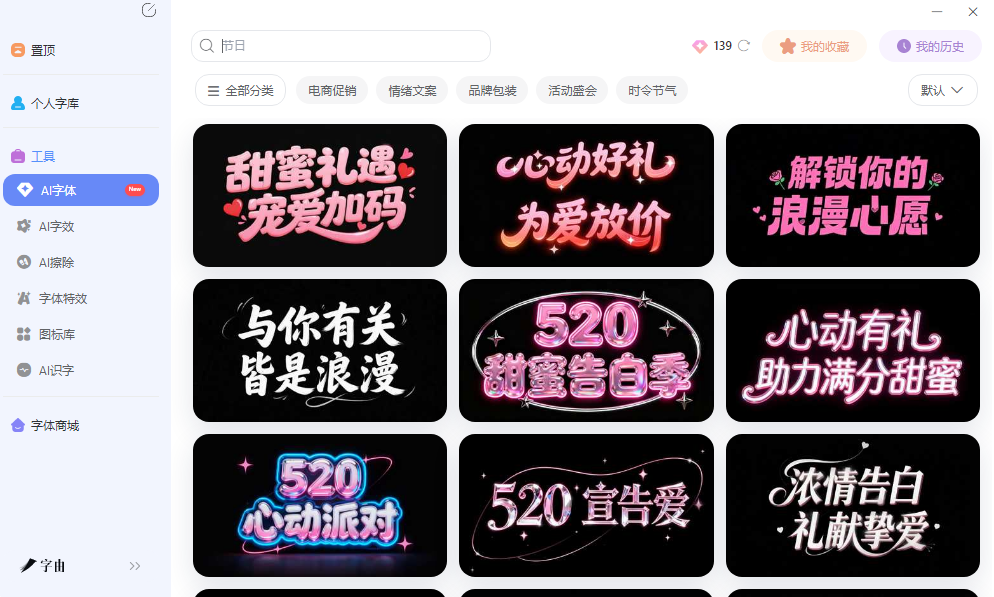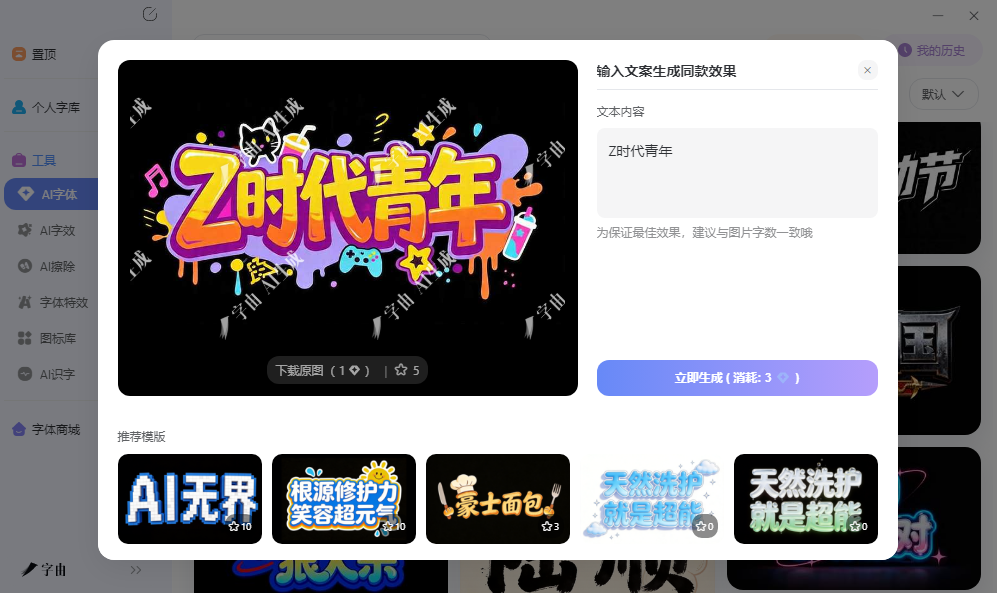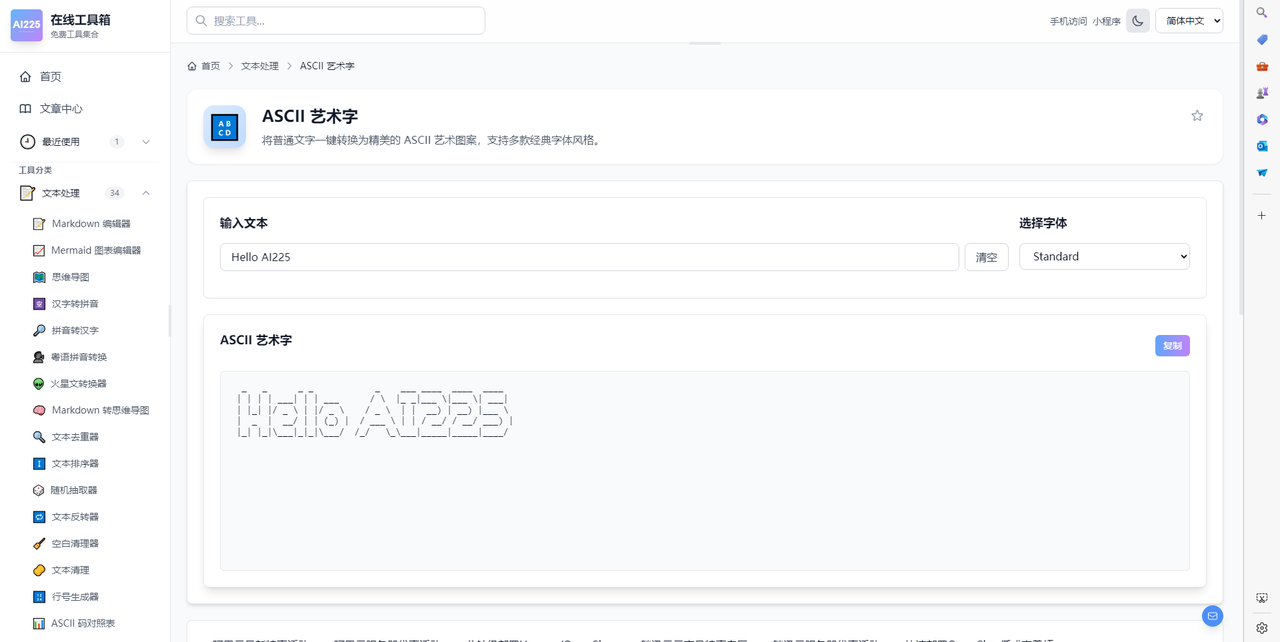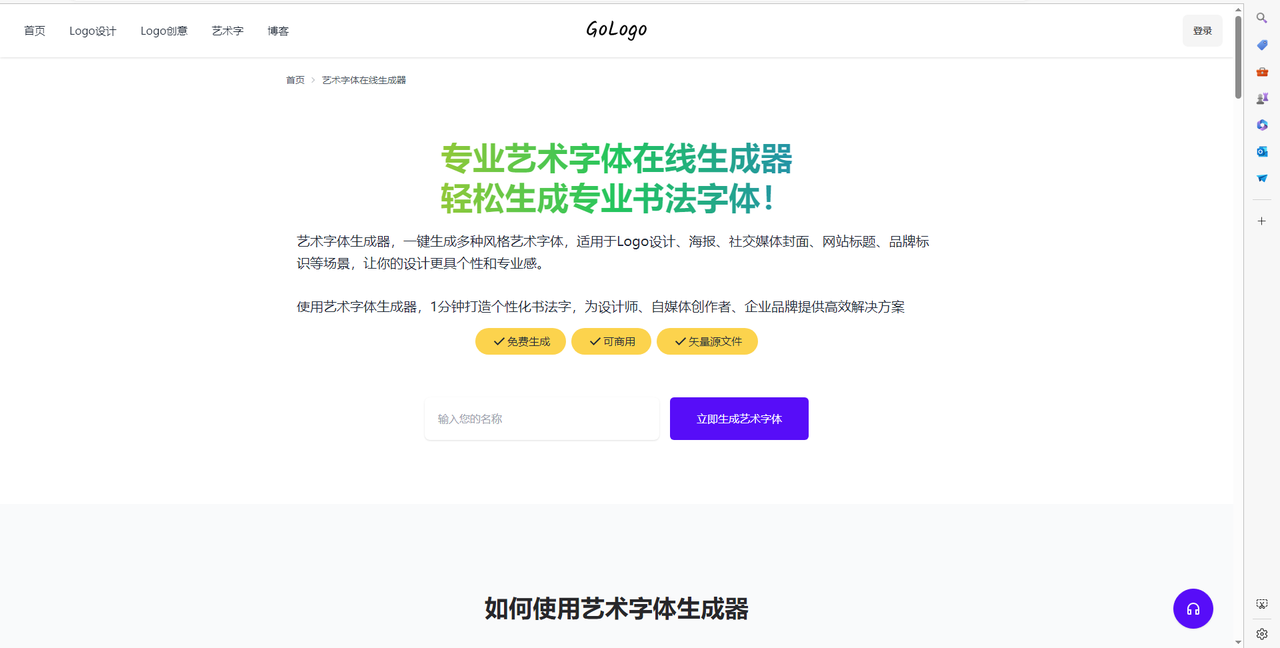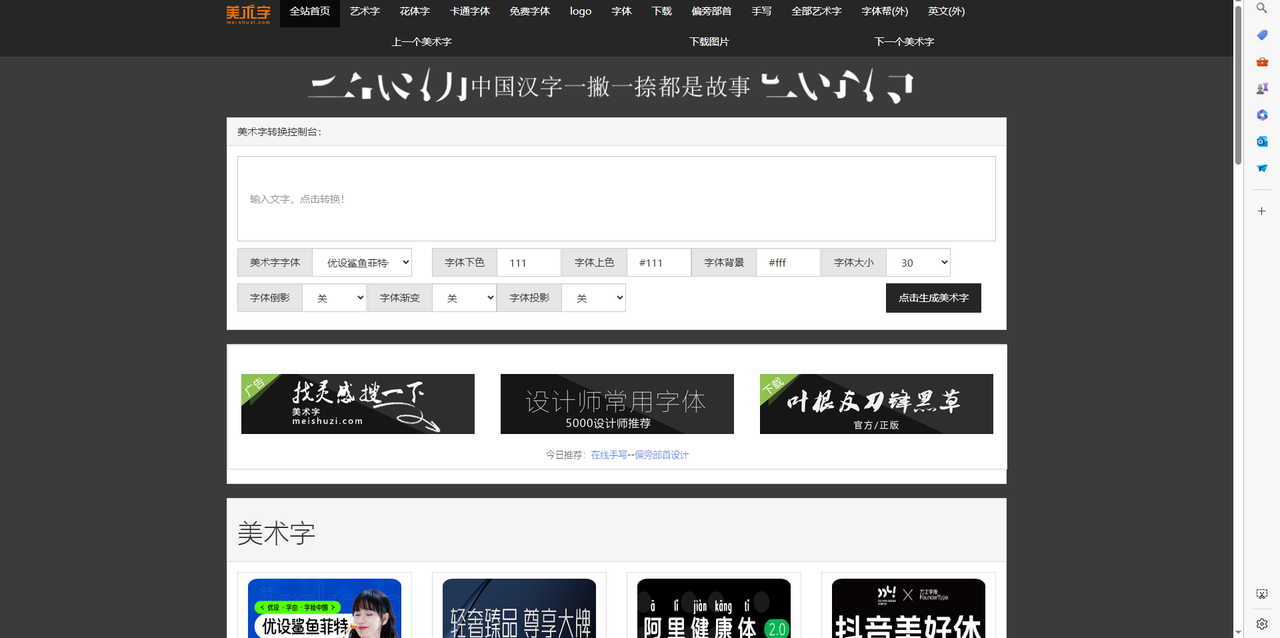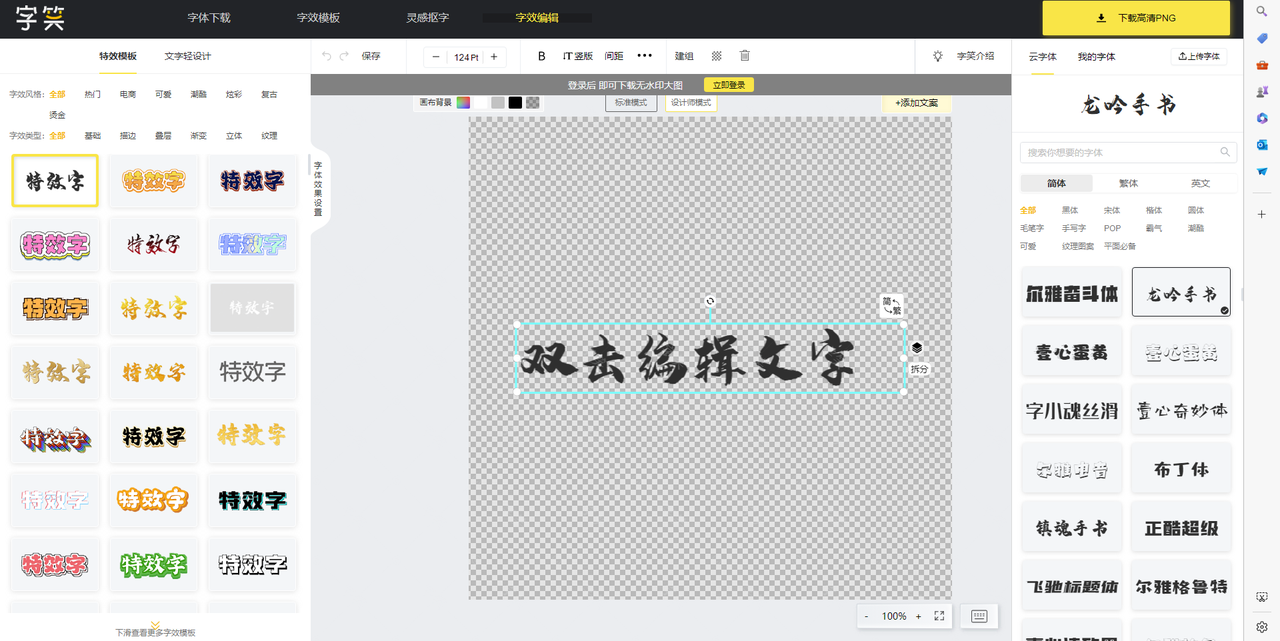
艺术字生成器免费用,不花钱也能出特效
如果你还在手搓艺术字的话那效率实在是太低了,如果是以前的话做一张海报,排版、配色都是需要时间的,但是做的时候发现系统自带的字体太死板,这时候就需要现成的艺术字生成器,输入文字,选个模板,几秒钟就能拿到一张带特效的标题图。不用学PS,不用调参数,甚至不用注册。今天挑了5款免费好用的工具,从字由的专业模板到ASCII字符画,从书法艺术字到可调参数的美术字,总有一款能解决你的问题。
我们第一个介绍的是字由,很多人知道字由是因为它有庞大的字体库,但它的AI字体功能才是做艺术字的捷径。打开字由客户端,在“AI工具”里找到“AI字体”,你会看到一个按场景和风格分类的模板库。国潮风、霓虹灯、金属质感、手写书法、电商促销……目前有400多套模板,每套都是专业设计师调好的字体+特效+排版的完整方案。
假设你正在做一张奶茶店的夏季促销海报,标题是“杨枝甘露”。你想让标题有点国潮感,但自己不会设计。打开字由AI字体,在风格筛选里点“国潮风”,翻到一款水墨晕染效果的模板,点击“做同款”。在右侧输入框把模板里的文字换成“杨枝甘露”,点“立即生成”。10到15秒后,一张带有水墨书法效果的艺术字图就出来了。下载透明背景的PNG,直接拖进海报里,整个过程不到一分钟。
字由的模板覆盖面很广。霓虹灯分类适合夜店活动、酒吧海报,每个字母都像真实的灯管弯曲盘绕;金属质感分类适合工业风、科技产品,拉丝金属、镜面金属、锈蚀金属都有;国潮风分类融合了书法笔触、水墨晕染、印章元素,适合茶叶品牌、中式餐饮;电商促销分类字重极粗、色彩鲜艳,双十一、618大促的海报标题直接从里面挑。如果你做的是英文标题,搜索“花体”“装饰”“英文书法”也能找到对应的模板。
2、ASCII艺术字
第二个工具是ASCII艺术字,来自AI225在线工具箱。它不生成彩色的特效字体,而是把普通文字转换成用字符拼出来的大字——就像上世纪BBS时代的字符画。输入“Hello AI225”,选择字体(Standard等),点击生成你会得到字符拼成的巨大字母。你可以复制这些字符,粘贴到代码注释、论坛签名、邮件尾巴、README文件里。如果你做技术博客、极客风格的海报、或者想给设计稿加点复古味,ASCII艺术字是别处找不到的效果。完全免费,无需注册。
3、GoLogo
第三个网站是GoLogo。它的“艺术字体在线生成器”主打书法风格艺术字,适合做Logo、海报标题、社交媒体封面。首页写着“√免费生成 √可商用 √矢量源文件”,对版权很友好。输入你的名称(品牌名或Slogan),点击“立即生成”,系统会给出多种书法艺术字方案。它支持自定义布局(水平、垂直、环绕)和颜色(传统墨色、朱砂红、金色等),生成后可以下载矢量源文件,放大不失真。如果你需要一款中式风格的标题字,或者给品牌做一个有手写温度的Logo,GoLogo比通用模板更对味。
4、美术字
第四个网站是美术字。它提供了一个美术字转换控制台,用户可以选择“美术字字体”(如“优设鲨鱼菲特”),调节字体下色、上色、背景、大小,还可以开关字体倒影、渐变、投影等特效。输入文字后点击“点击生成美术字”,就能得到一张定制化的艺术字图片。这个工具比纯模板生成更灵活——你想要倒影效果就打开倒影,想要渐变色就打开渐变。适合那些“想要一点特效,但又不想从头学PS”的用户。页面还推荐了“叶根友刀锋黑草”“阿里健康体2.0”等热门字体,可以直接参考。生成结果可以下载图片,免费使用,但商用建议先确认字体授权。
5、云字体平台
第五个网站是一个云字体平台。它提供了字效模板分类:基础、描边、叠层、渐变、立体、纹理等。用户可以在画布上添加文案,选择字体(如“龙吟手书”“瓦雅蕾斗体”“壹心蛋黄”“布丁体”“镇魂手书”等),点击特效模板即可实时预览效果。还支持字体搜索(黑体、宋体、楷体、圆体、毛笔字、手写字、POP等)和画布背景调整。编辑完成后可以下载高清PNG图片(登录后无水印)。这个平台的模板数量多,而且分类清晰,从中文到英文都有。
五款艺术字生成器,用法各不相同。字由最适合设计师和需要快速出专业级特效图的人,400多套模板覆盖国潮、霓虹、金属等风格,10秒出图,;ASCII艺术字走复古极客路线,把文字转成字符拼图,适合技术社区和个性签名;GoLogo专注书法艺术字,可商用还支持矢量下载,适合做Logo和品牌标题;美术字可调倒影、渐变、投影等参数,比纯模板更灵活;云字体平台模板数量多,支持实时编辑和下载,适合批量尝试不同风格。不管你是赶项目的电商运营,还是想做一张不一样的朋友圈配图,总有一个工具能帮你把普通文字变出不一样的效果